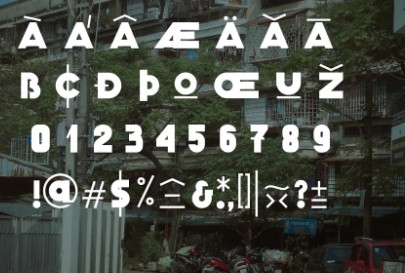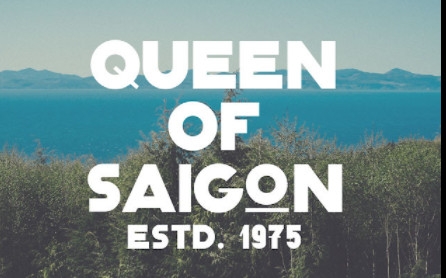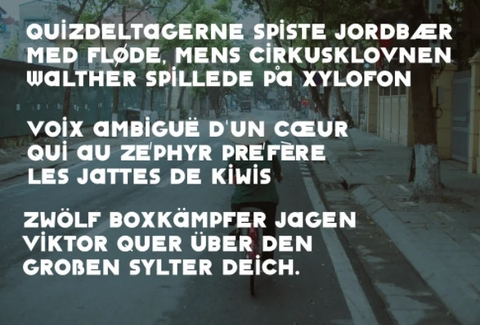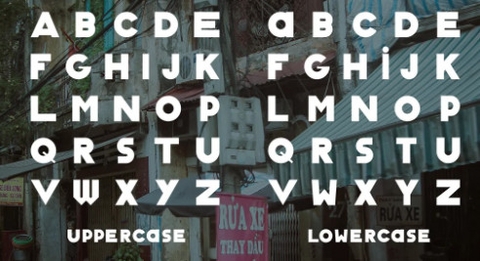
In An Anh chia sẻ đến tất cả các bạn một font việt hóa siêu đẹp, mang phong cách vintage, retro, đậm nét Hồ Chí Minh – Hòn ngọc viễn đông ngày ấy – Classique SaiGon.
Người ta xây dựng thích nét truyền thống từ những tấm bảng hiệu viết tay của tp Hồ Chí Minh vào các thập kỉ trước . Từ niềm đam mê và cảm xúc tích cực đó, Classique SaiGon đã xuất hiện nhằm lưu lại và truyền bá phông chữ đặc sắc có từ xưa đời này của nước ta.
Tuy nhiên Classique SaiGon không chỉ xây dựng lại y đúc mẫu chữ thời kỳ trước, mà lại được sáng tạo ra nét tối tân kết hợp với sự cổ truyền rất dấu ấn. Font việt hóa này khả dụng trong các xây dựng mang tính retro, phong cách truyền thống, đương nhiên nhiều khả năng dùng cho cho bất kỳ cách thức nào như banner, backdrop, brochure, bức ảnh fanpage, xây dựng áo, và đặc biệt sử dụng trong typography là siêu ổn !
Tác giả của font Classique SaiGon là ai?
Cho dù được gọi là font Classique SaiGon tuy nhiên bộ font này lại do một anh chàng người thủ đô. sáng tạo nên. anh chàng ấy tên là Mạnh Nguyễn , một designer rất say mê những biển quảng bá. pa-nô thời trước, niềm say mê ấy đã thúc đẩy chàng quyết chí thi hành dự án . Theo phong cách Hồ Chí Minh xưa cũ. Và bộ font Classique SaiGon đã xuất hiện trong bối cảnh ấy
Giới thiết kế đều thú nhận rằng, phong cách vintage và retro hiếm khi nào lạc hậu. vừa truyền thống lại mang nét gì đó phù hợp với thời đại . đôi bên đều chẳng lúc nào bị quên lãng, mà lại giúp các designer tạo cho mình nét độc đáo riêng cho những sản phẩm của bản thân.
Bộ font Classique là minh chứng chi tiết nhất cho khía cạnh này. Chỉ cần nhìn vào bộ phim cô ba tp Hồ Chí Minh, một bộ phim điện ảnh có tiếng của nền điện ảnh nước ta. Dùng bộ font Classique SaiGon đủ thấy sức tác động của bộ kiểu chữ này.